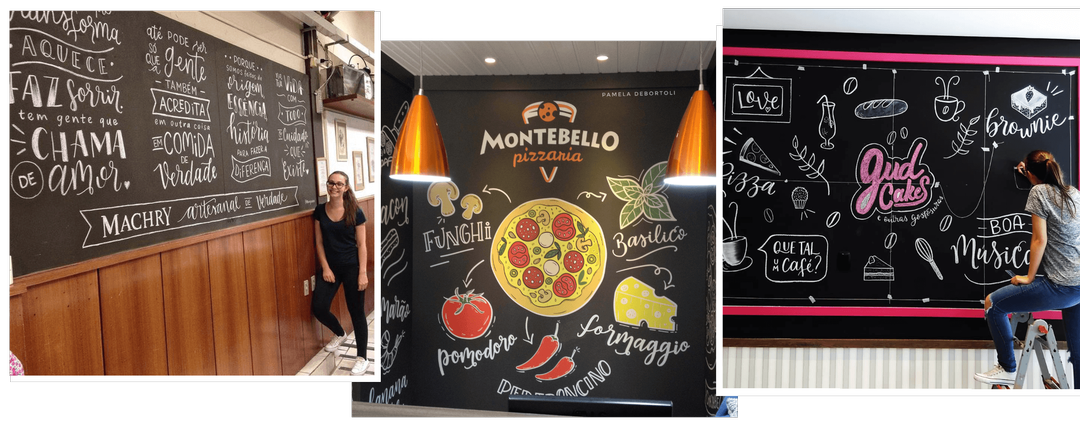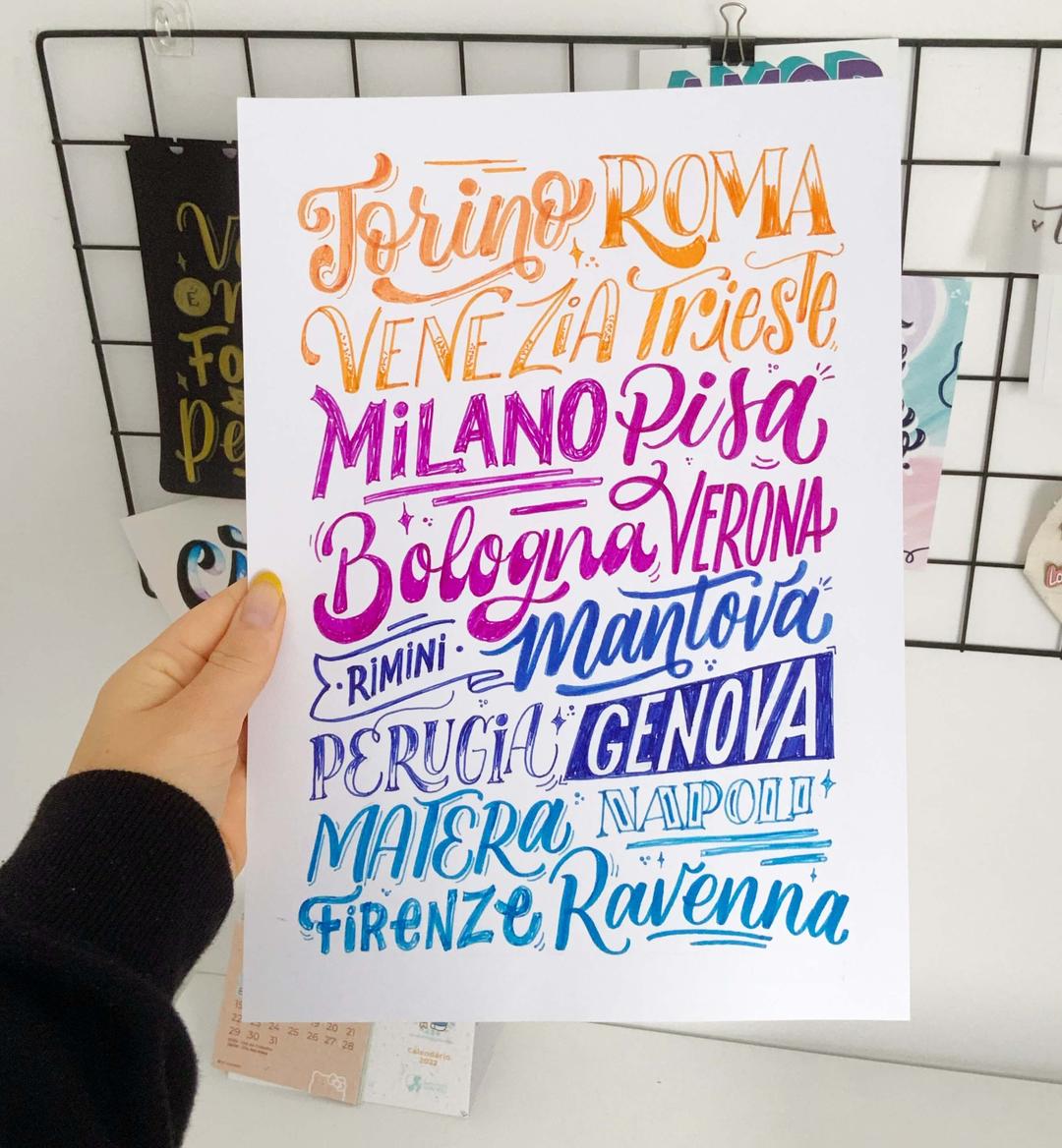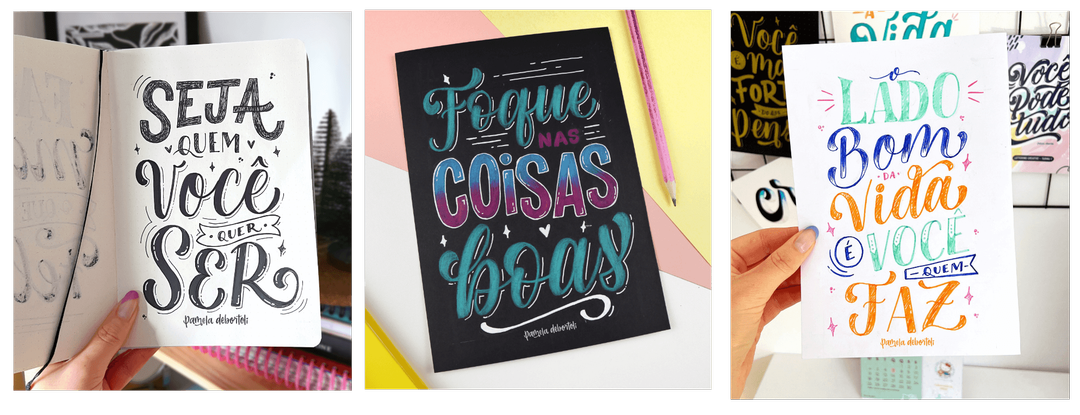
O que é lettering? Como funciona? Por onde começar?
Lettering: A arte de desenhar letras
Lettering é a arte de desenhar letras e palavras visualmente bonitas e chamativas, as artes de lettering são sempre na sua maioria feitas a mão. É uma habilidade que existe a séculos, com calígrafos que antigamente escreviam a mão de uma forma elegante livros e documentos.
Hoje a arte do lettering evoluiu e está mais moderna e com um maior leque de possibilidade tanto nos materiais para desenvolver a arte quanto nas possiblidades do que pode ser criado, a arte do lettering é muito usada no design de um modo mais digital para a criação de logotipos, convites, capa de livros, ou de uma forma mais analógica feito a mão como quadros, e pode ser feito ou aplicado em diferentes tipos de superfícies, como em paredes, personalizando porcelanas, tecidos, etc.
O que é Lettering?
Antes de começar a explicar o que lettering, vamos falar um pouco sobre caligrafia e tipografia.
A Caligrafia também é conhecida como a "arte da bela escrita", é a técnica de escrita a mão formando letras elegantes e harmônicas, existem muitos estilos de caligrafia, mas as mais conhecidas são a gótica, itálica e a romana. Esse estilo de escrita é sempre feito a mão e direto com a pena, sem antes fazer um rascunho das letras ou frases, antigamente os livros e documentos eram escritos desse modo.
Já a tipografia faz uso de fontes e letras pré-existentes. Um designer de tipos cria alfabetos completos onde cada letra é pensada e criada para que quando for usada em conjunto, trabalhe de maneira harmônica com todas as outras letras desse alfabeto independentemente da ordem em que elas forem usadas e tudo isso com uma ótima legibilidade.
As fontes tipográficas podem ser usadas infinitas vezes e para projetos de diferentes estilos. Elas fazem parte do nosso dia a dia, encontramos em livros, jornais, quando estamos escrevendo um texto no computador e nos nossos celulares.
O Lettering é a arte de organizar e desenhar letras e palavras de uma forma legível e esteticamente agradável. Envolve o use de vários materiais e técnicas diferentes para criar um estilo único e que tenha um grande impacto visual. O lettering é normalmente feito à mão e nós permite ter mais liberdade criativa e de expressão e tem como objetivo contar uma história, transmitir uma mensagem ou uma ideia através do desenho das letras.
As letras são desenhadas do zero, como se cada uma fosse uma mini ilustração, sendo assim algo único e personalizado e é isso que traz tanto valor para essa arte.
Existem muitos estilos diferentes de letras, desde aquelas que tem uma aparência e regras bem semelhante as da caligrafia, como o estilo de letra cursivo com variação de espessura, e outros estilos que são parecidos com fontes tipográficas, mas claro que precisamos sempre nos lembrar que a arte do lettering é sempre com letras desenhadas, de uma forma mais moderna e decorada.
Materiais mais usados e técnicas:
Para criar lettering, artistas e designers usam uma variedade de materiais e técnicas, dependendo de seu estilo e meio preferidos. Algumas das ferramentas mais comuns incluem:
• Canetas: de longe esse é o material mais usado no lettering, aqui não existe regras, você pode usar qualquer tipo de caneta com qualquer estilo de ponta, pode ser desde uma caneta esferográfica até uma caneta super chique com ponta fina ou grossa.
Esse é o meu material favorito e que uso sempre nos meus lettering, você pode usar canetas coloridas para destacar e deixar toda a composição do lettering ainda mais interessante e bonita, ou finalizar a arte usando apenas uma caneta preta, vai do seu mood e gosto pessoal.
• Lápis de cor: Os lápis de cor são outro tipo de material que você pode usar nos seus letterings, é uma ótima opção para quem gosta de artes coloridas, com uma caixinha de lápis vocês terá uma infinidade de opções e combinações de cores.
• Pincéis: Os pincéis são uma escolha popular para criar letterings maiores e podem ser usados com uma variedade de meios, incluindo aquarela, tinta.
Além dos materiais usados, existem muitas técnicas e estilos diferentes de lettering, incluindo:
• Lettering cursivo: Este estilo como comentei antes ele imita a escrita da caligrafia. Dentro do estilo cursivo temos 3 estilos de letras, as letras cursivas com variação de espessura, as com espessura fixa, e o estilo fat bottom.
• Letras com serifas: As serifas são as pequenas linhas ou traços no final das principais hastes de uma letra, e esse estilo é caracterizado pela presença desses traços. Esse estilo é muito semelhante aquele usado em materiais impressos como livros e jornais.
• Letras sem serifas: Este estilo não tem os pequenos traços e prolongamentos no final das hastes das letras e é frequentemente usado para designs modernos e minimalistas.
A versatilidade do lettering o torna uma ferramenta valiosa para qualquer designer ou artista que queira adicionar um toque pessoal ao seu trabalho.